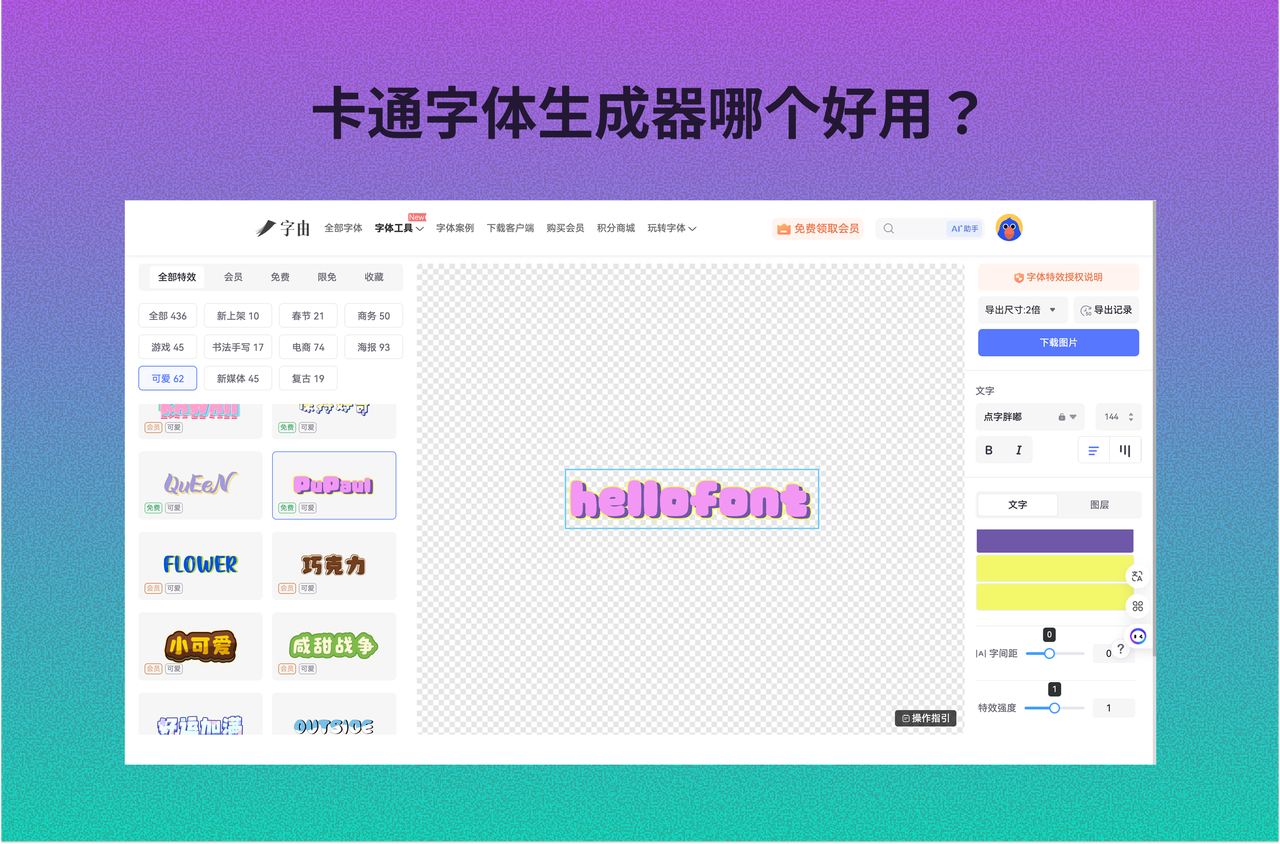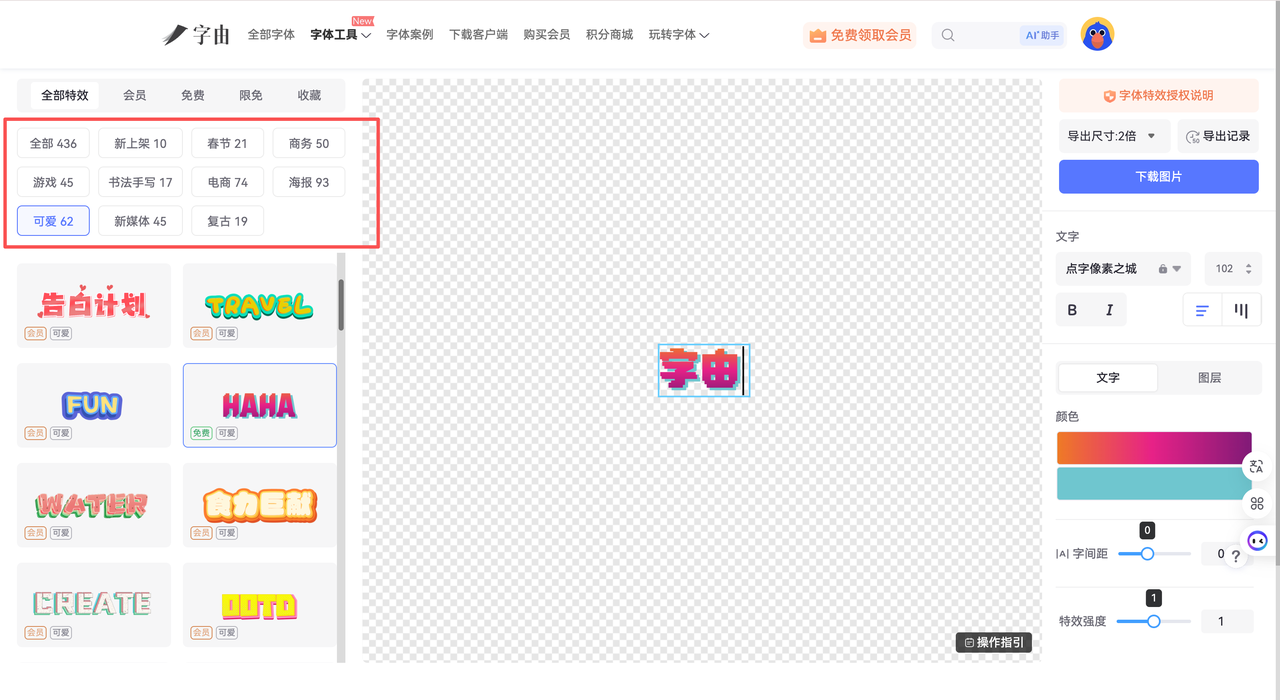
卡通字体生成器哪个好用?4款免费工具实测推荐
你有没有发现,现在很多海报、短视频封面、甚至电商Banner,都越来越“可爱”?卡通字体生成器这类工具为什么这么火?根据 Adobe 的趋势报告,视觉设计正在向“情绪化表达”发展,字体风格对用户感知影响明显提升。换句话说,一个可爱字体生成器生成的标题,可能比图片更吸引人。我现在做卡通风设计,一般分三步走:第一步,用工具快速生成基础风格;第二步,筛选出“可优化”的字体;第三步,在设计软件中微调。关键在第一步——你用什么工具,决定了后面效率差多少。下面这些,是我现在还在用的,教你快速生成一个好用、可商用的卡通字体。
1 、字由——可生成+可应用的卡通字体生成器
如果你是设计师,我最推荐的其实是字由。很多人以为它只是字体管理工具,其实它也可以当作一个免费卡通字体在线生成工具使用,而且体验比普通工具更完整。我之前做一个儿童活动海报,需要设计6个标题模块。如果全部手动设计,大概需要1小时以上。但用字由先生成基础卡通字体效果,再稍微优化,大概20分钟就完成了。这种效率提升,在做多页面设计时特别明显。
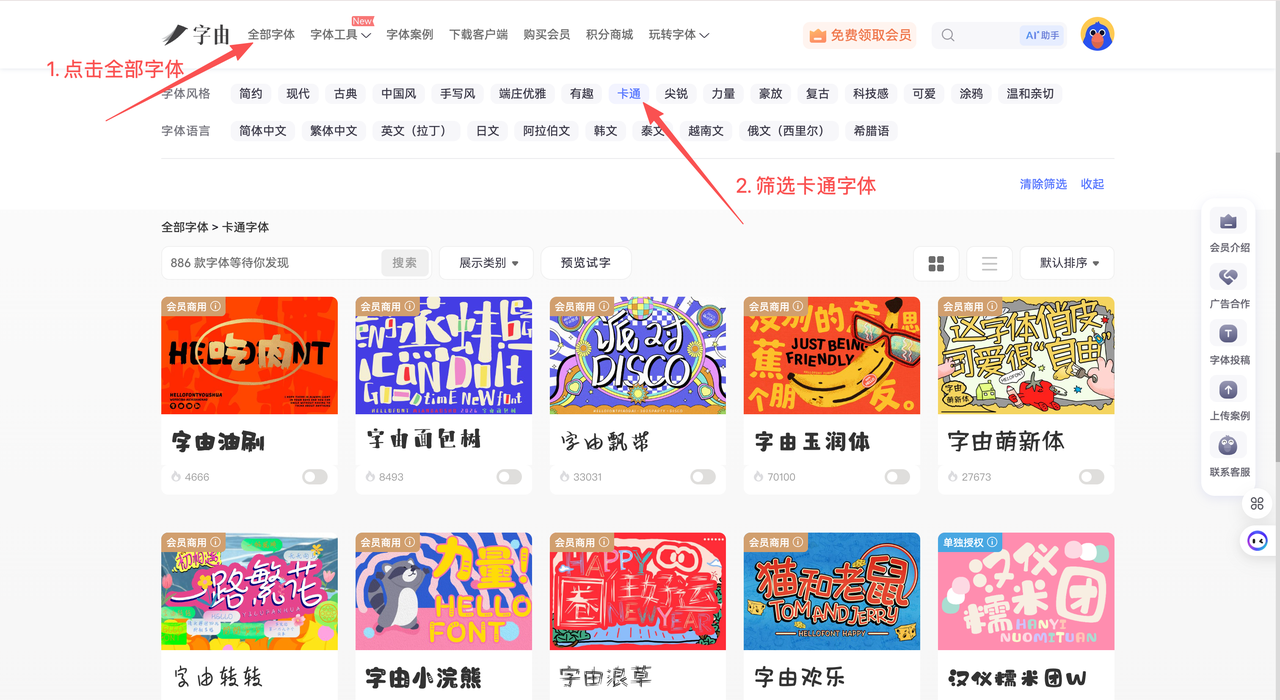
用字由生成卡通字体(详细步骤)
第一步,打开字由客户端,进入「字体特效」功能。
第二步,在输入框中输入你的文字,比如活动标题或品牌名称。
第三步,在风格分类中选择“卡通 / 海报 / 新媒体”等标签。
第四步,挑选一个喜欢的卡通字体效果,比如气泡字体、手写卡通字体。
第五步,调整颜色、阴影、字间距和特效强度,让字体更贴合你的设计。
第六步,一键导出PNG,或者直接在PS/Figma中应用字体。
2、Cool Text——经典可爱字体生成器
Cool Text 是一个老牌工具,适合快速生成简单卡通字体。它的使用方式很直接:输入文字→选择样式→下载图片。生成速度很快,几秒钟就能完成。我早期做论坛封面时用过很多次,尤其是做“卡通标题”或“游戏风字体”时,效果还不错。但问题也很明显:风格比较老,不太符合现在的2026卡通字体在线趋势。
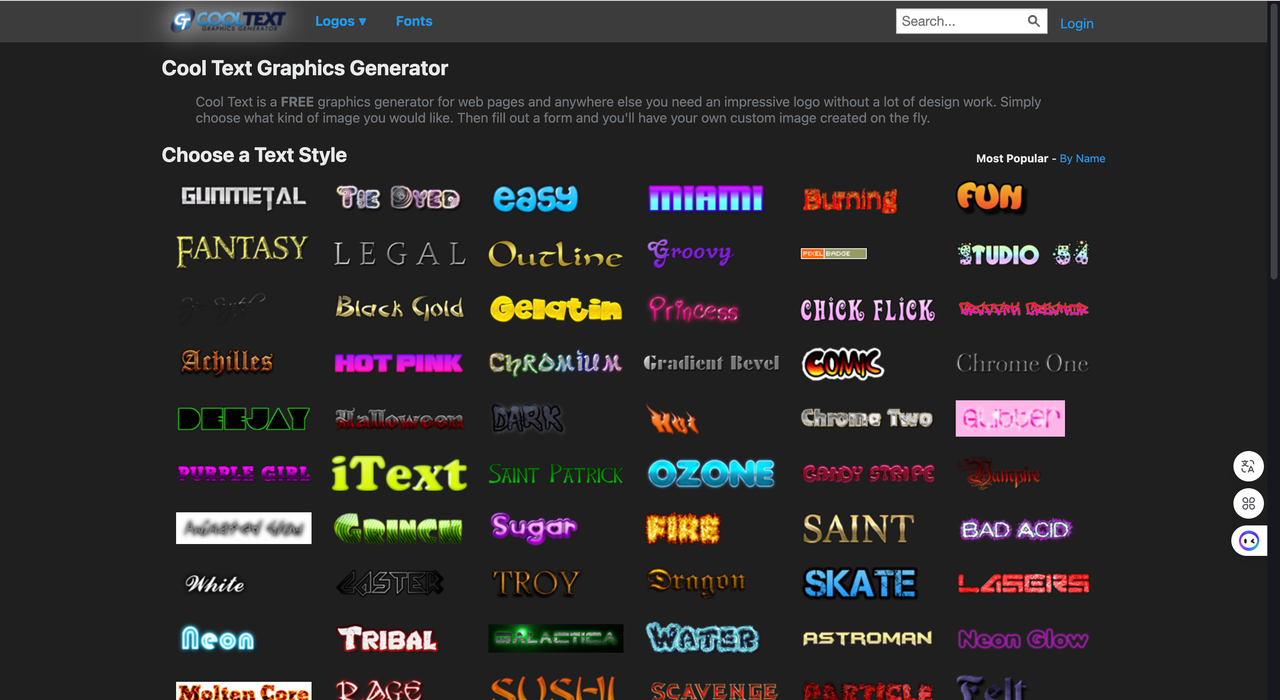
3、Flaming Text——偏Logo的卡通字体生成器
这个工具更偏向Logo生成。如果你需要做一个可爱品牌标题,比如儿童品牌、甜品品牌,它的效果会比较适合。不过自由度没有那么高,更多是模板式生成。
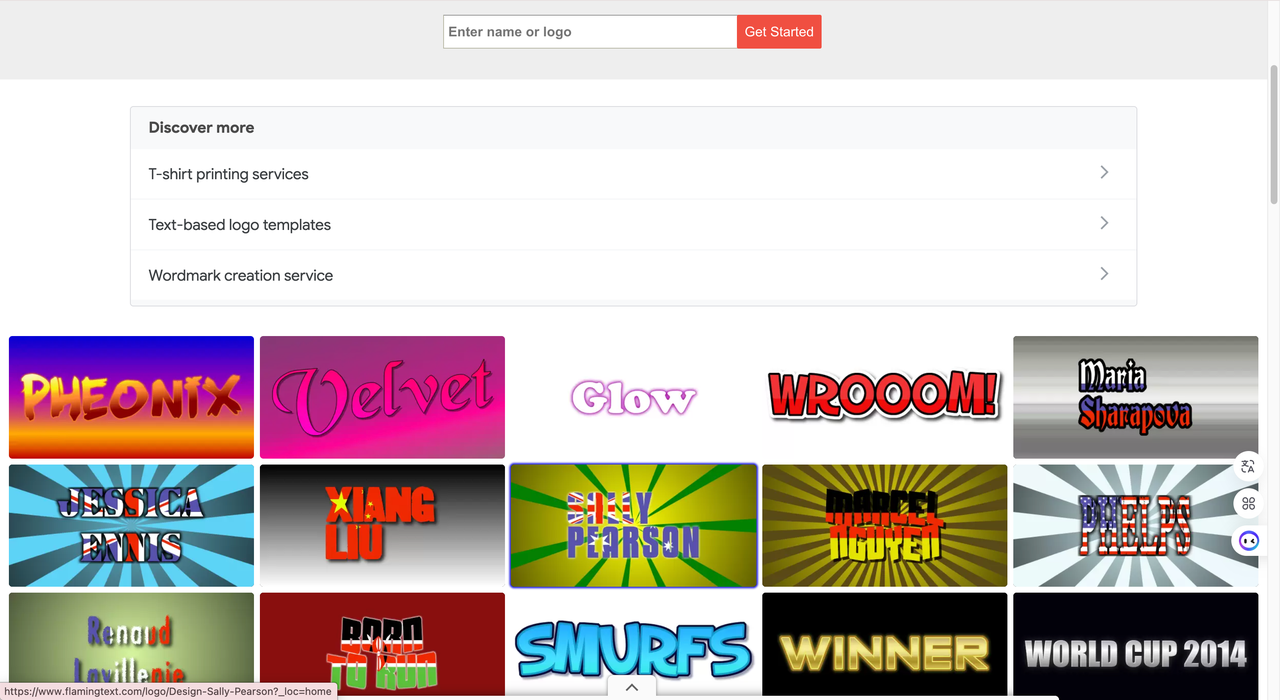
4、Canva——适合新手的卡通字体在线工具
如果你不是设计师,只是想快速做封面或社交媒体图片,Canva会更友好。它内置很多卡通免费字体,直接拖拽就能使用,而且还能搭配模板。它不需要你懂设计。你可以直接用模板,然后替换成卡通免费字体,再稍微调整一下,就能出一个不错的封面图。我之前带一个运营同事做封面图,他基本不用PS,全靠Canva完成。
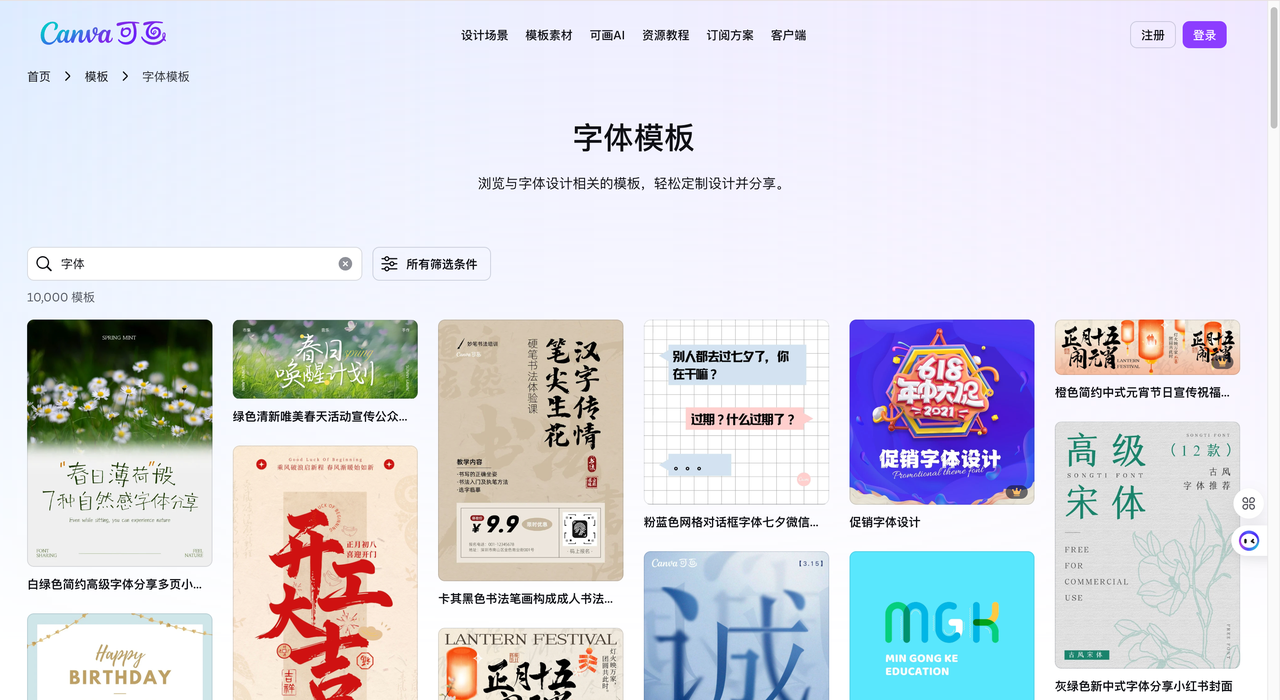
卡通字体设计的3个经验
说实话,卡通字体不是越可爱越好。我见过很多设计,问题不是字体不够花,而是太花。
- 第一个建议:卡通字体尽量控制在标题使用,不要全页面使用。
- 第二个建议:注意配色。卡通字体如果颜色太杂,会显得廉价。
- 第三个建议:字距很关键。稍微拉开一点,会更有“呼吸感”。
现在卡通字体其实在变得更“精致”。不再是单纯的夸张,而是:更干净、更有品牌感、更适合商业使用。这也是为什么像字由这种工具,会把卡通字体生成器和字体管理结合起来。如果你只是偶尔用一下,简单的免费卡通字体在线生成工具就够了。但如果你经常做设计,我更建议你用像字由这种工具。因为真正重要的不是你有没有字体,而是你能不能真的快速上手用起来。